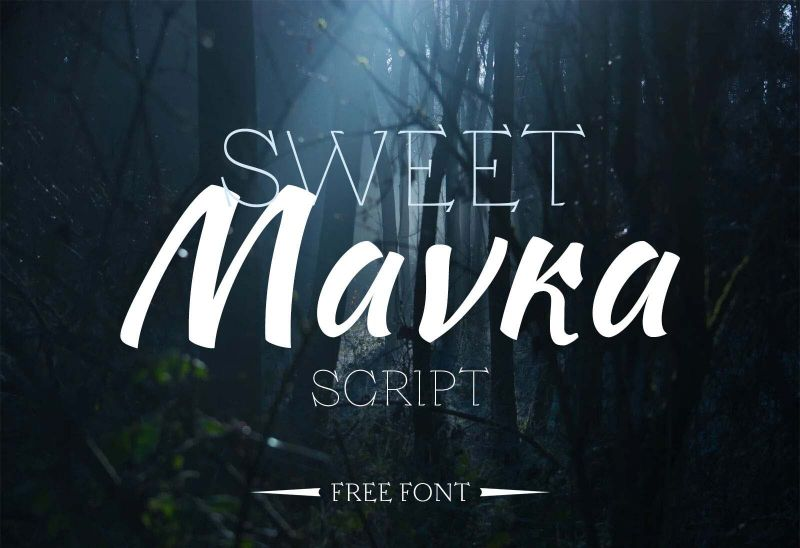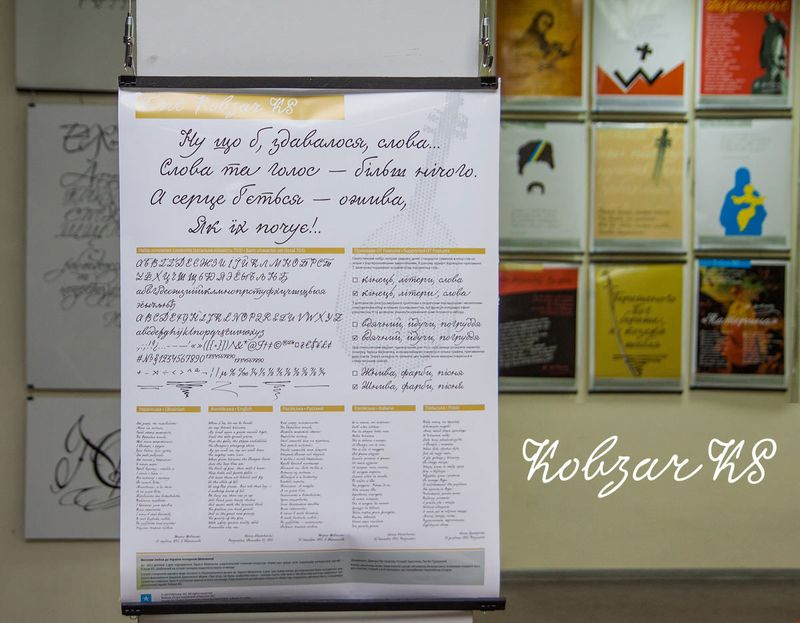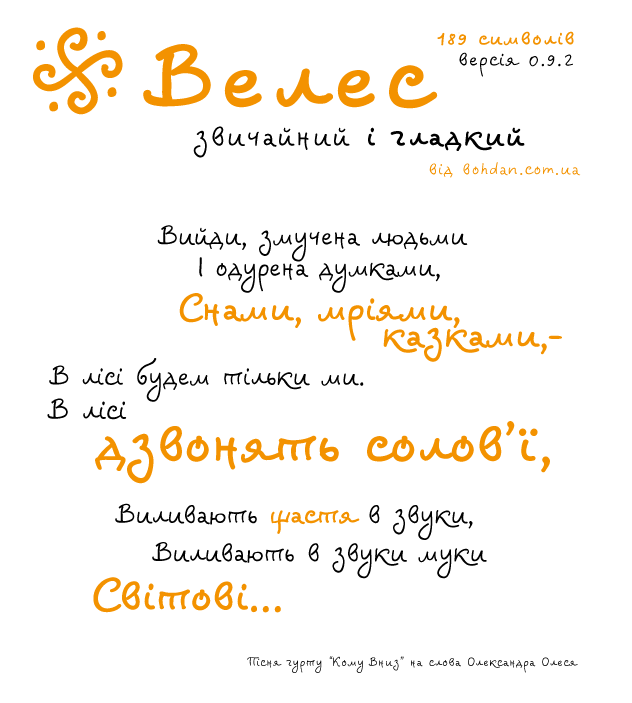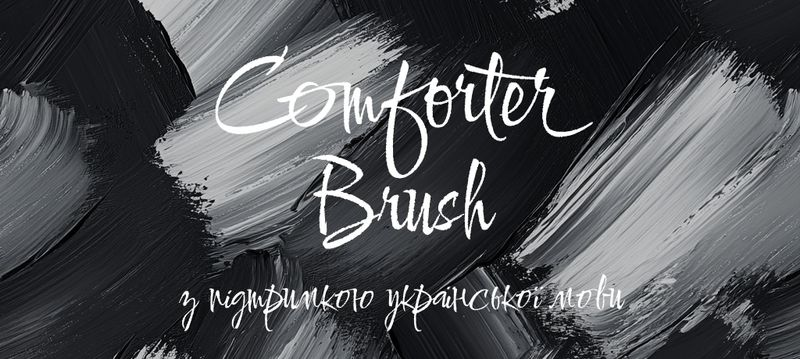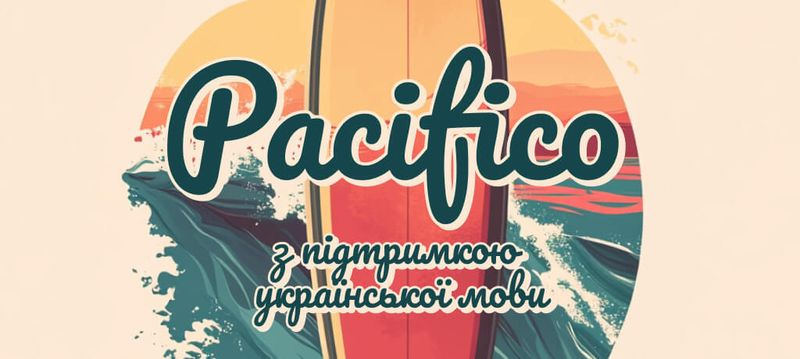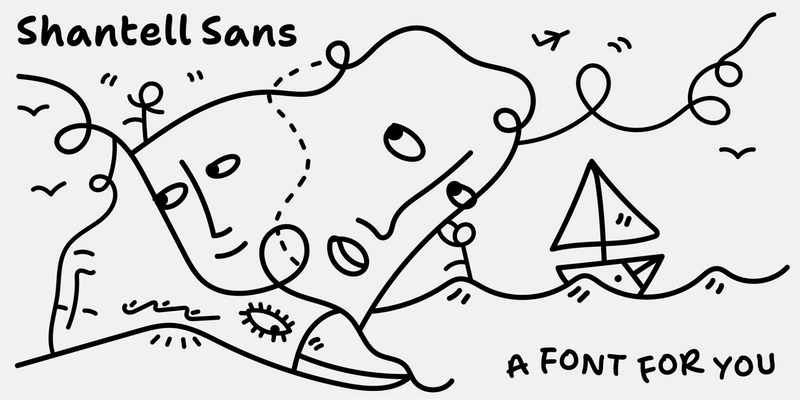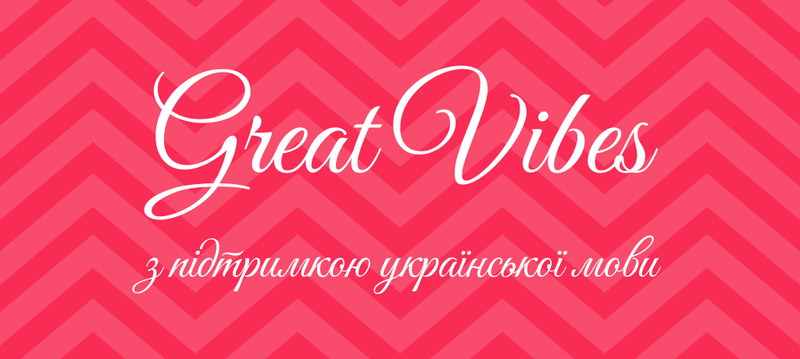
Безкоштовні рукописні шрифти з підтримкою української мови
Добірка стильних рукописних шрифтів з підтримкою української мови
Шукаєте стильні рукописні шрифти, які підтримують українську мову? Ми зібрали для вас декілька цікавих варіантів, які зможуть додати вашим проєктам унікальності та витонченості.
Шрифт Sweet Mavka Script
Мавка — загадкова істота з українських легенд. Вони любили квіти, носили їх у волоссі й заманювали хлопців навесні в гори, де ті знаходили свою смерть.
Шрифт Sweet Mavka Script це стильний і витончений шрифт, підтримує як латиницю, так і кирилицю. Він універсальний і виглядає чудово у будь-якому розмірі. Його можна використовувати для брендингу, дизайну інтер’єрів, упаковок, заголовків у журналах або для стильних текстових вставок на фото. Шрифт доступний для безкоштовного особистого використання.
Шрифт Kobzar KS
До 200-річчя з дня народження Тараса Шевченка Kyivstar створив подарунок для українців — шрифт Kobzar KS. Він передає почерк нашого легендарного поета і художника.
Шрифт простий у використанні, але дуже виразний. Цей шрифт — ключ до українського культурного коду, до розуму і творчості Тараса. З Kobzar KS кожен може виразити любов до рідної землі, віддати шану традиціям і зберегти культурну спадщину. Шрифт безкоштовний для завантаження і використання згідно з ліцензією.
Шрифт Велес
Основою цього стилю став український скоропис, який був не просто відтворений, а переосмислений по-своєму з сучасним поглядом на нього.
Шрифт доступний у двох накресленнях: звичайному (regular) та гладкому (bold). Ви можете використовувати шрифт для некомерційних і комерційних проектів.
Шрифт Comforter Brush
Comforter Brush — це стильний «пензлевий» шрифт, який має сучасний, легкий та динамічний характер. Comforter Brush створений у формі рукописного стилю, але з власною сучасною інтерпретацією. Він нагадує легкі мазки пензля, що додає тексту живості та унікальності.
Шрифт Pacifico
Pacifico — це яскравий, оригінальний шрифт, створений у стилі пензлевого написання. Шрифт натхненний атмосферою американської серф-культури 1950-х років. Уявіть собі сонячні пляжі, хвилі та легкість життя — усе це відчувається у цьому шрифті.
Pacifico — це не просто шрифт, це настрій, свобода і трохи ретро-шарму.
Шрифт Shantell Sans
Британська художниця та філософ Шантель Мартін відома своїми роботами, в яких вона активно використовує слова. Її мистецтво прикрашає Oculus у Всесвітньому торговому центрі в Нью-Йорку. Її роботи бачили і на екранах Таймс-сквер, і на сцені Лінкольн-центру, де виступає Нью-Йоркський балет.
У шкільні роки Шантель боялася диктантів та перевірок на правопис. У свої двадцять років вона зрозуміла, чому читання й письмо давалися їй так важко. Це відкриття стало початком її подорожі до створення шрифтів та роботи з текстом.
Шрифт Great Vibes
Great Vibes — це шрифт, що зачаровує своїм плавним та витонченим стилем письма. Верхні літери мають легкий і невимушений вигляд, тоді як нижні виглядають більш класично й формально. Таке поєднання робить текст живим, красивим і легко помітним.
Шрифт має спеціальні лігатури, що роблять з'єднання літер більш м'якими, є альтернативні символи. Текст можна робити ще більш унікальним і гратися з його виглядом.
Він ідеально підходить для проєктів, де потрібно передати елегантність, легкість і трохи чарівної атмосфери в тексті.